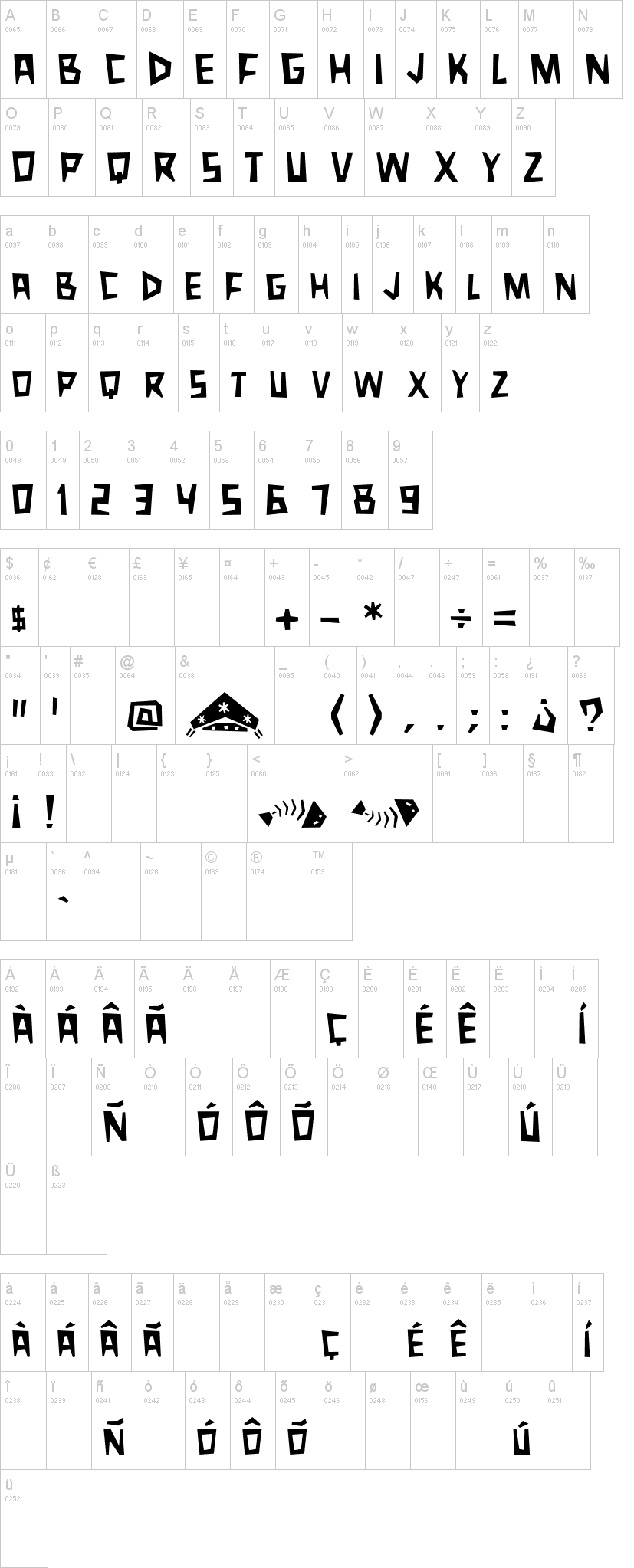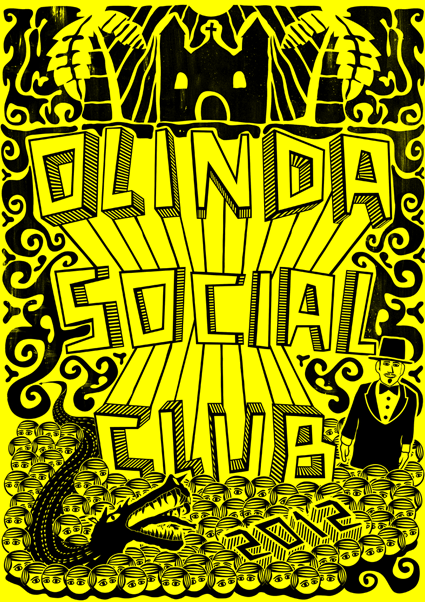
Шрифт Xilosa
Esta fonte é uma re-leitura da escrita de xilogravura característica da literatura de cordel* do nordeste brasileiro. Nas pesquisas em livretos de cordel, pode-se observar que os carecteres possuem arestas bem definidas, mesmo que não formassem alguma forma geométrica regular. Dessa forma, a Xilosa mantém essa característica irregular dos caracteres, com uma leitura mais firme ( deixando de lado o efeito rebuscado resultante da gravação do xilo), dando um aspecto mais moderno ao caractere, sem deixar de perder o charme e o regionalismo do cordel nordestino.
* gênero literário popular escrito frequentemente na forma rimada. Tradição originada em relatos orais e depois impresso em folhetos.
Esta tipografía es una interpretación de la aplicación de la xilografía en la Literatura de Cordel* en el nordeste de Brasil. En el material literario del Cordel, se puede observar carecteres con bordes bien definidos, aunque sin formar geometrías regulares. Por lo tanto, XILOSA mantiene la característica de lo irregular, con una lectura más firme (dejando de lado el resultado rebuscado del grabado en madera), dando un aspecto más moderno a la tipografía, sin preder el encanto y el regionalismo del Cordel Nordestino.
* género literário popular escrito frecuentemente en forma de rima. Tradición originada de los relatos orales y luego impresa en folletos.